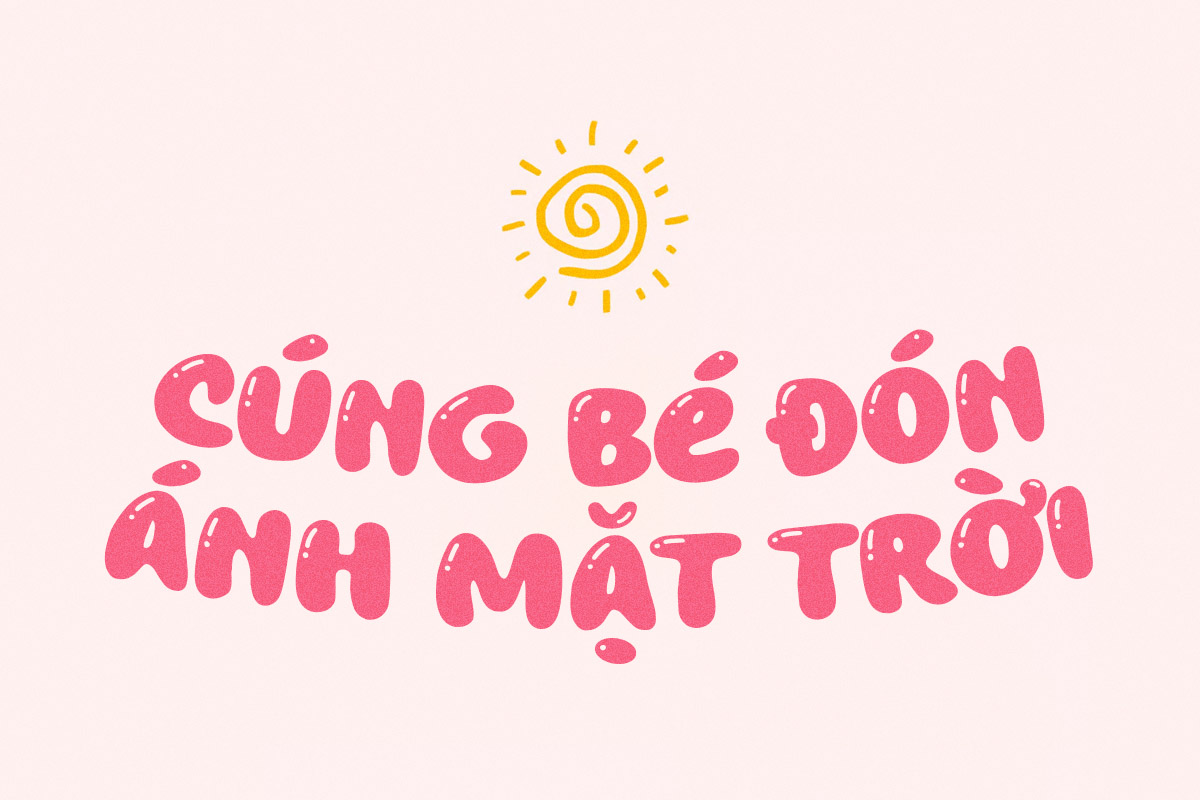
Trong thiết kế, font chữ là linh hồn của cảm xúc thị giác, và việc lựa chọn đúng font chữ béo Việt hóa có thể biến một ý tưởng đơn giản thành thiết kế nổi bật, vui nhộn và dễ ghi nhớ. Bộ sưu tập Top 10 font chữ béo, font chữ mập Việt hóa đẹp nhất 2025 từ Fontdep.vn không chỉ hỗ trợ đầy đủ dấu tiếng Việt mà còn mang đến sự sáng tạo trẻ trung, phù hợp cho poster, logo, bao bì, mạng xã hội và thiết kế hoạt hình.